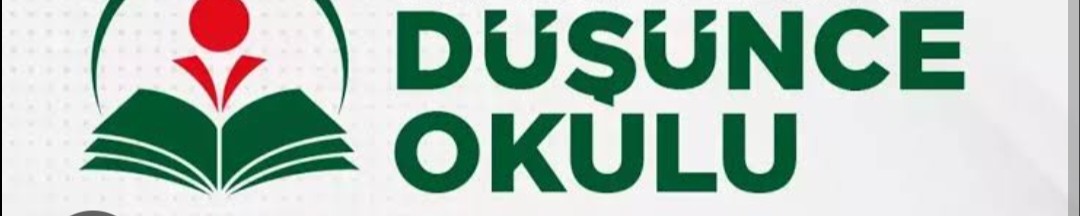
Font hakkında yardım
Selam arkadaşlar şu tarz kesik hazır font var mı acaba, tek tek uğraştırıyor insanı 😂
Bu fontları bir inceleyin, umarım işinize yarar hocam.
Dolcissimo Rough
TT Norms Pro Expanded ExtraBold
Gravesend Sans Heavy